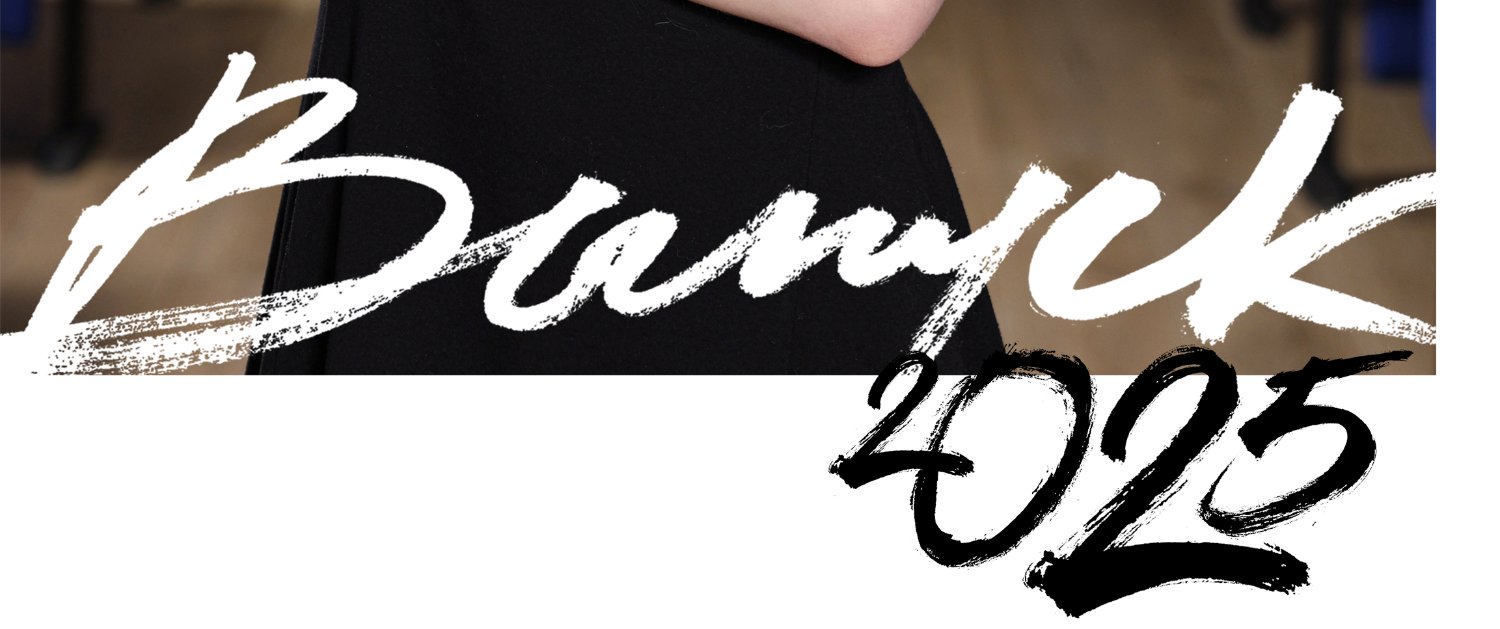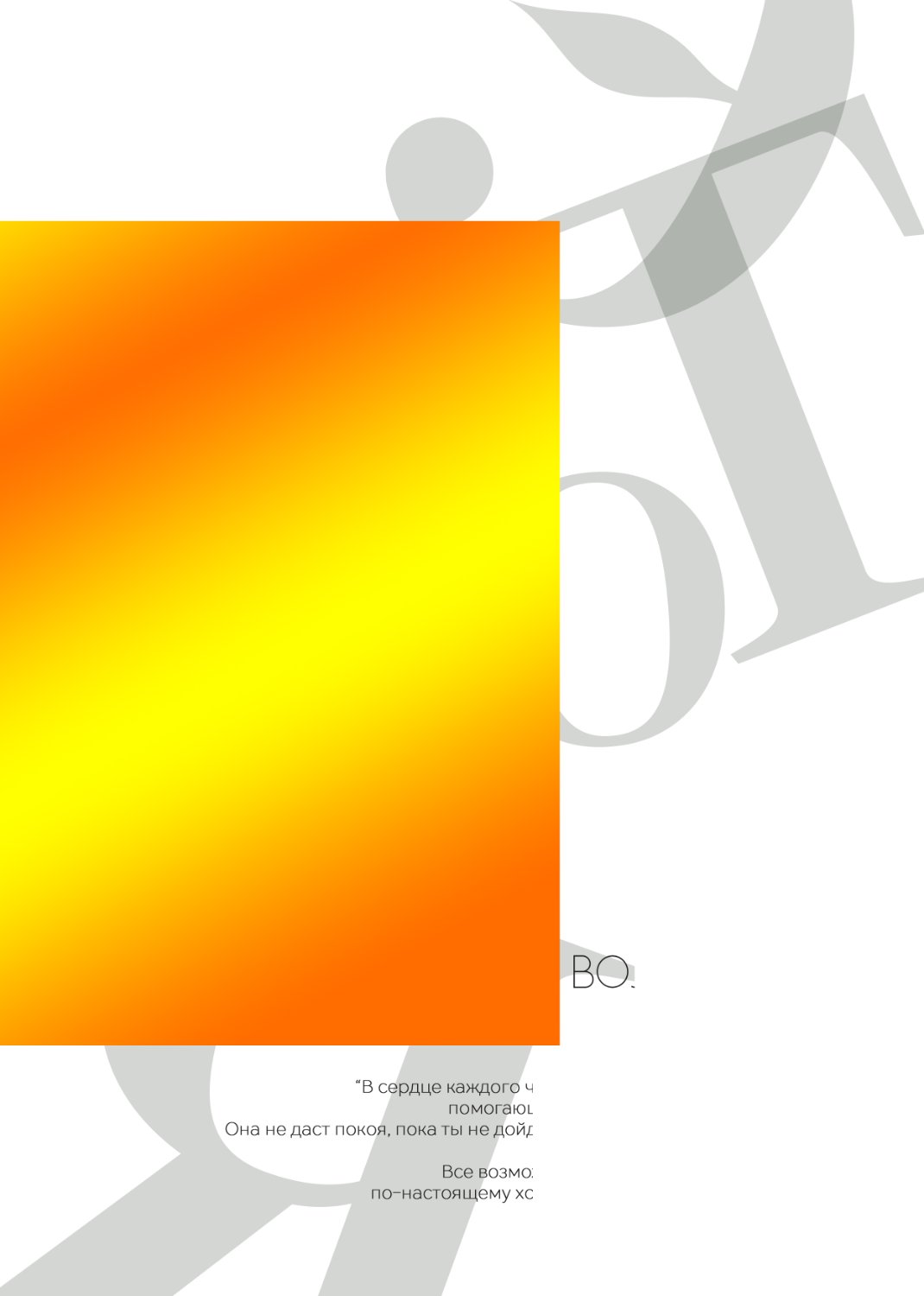
Помогите найти шрифты
Здравствуйте! Помогите пожалуйста найти шрифты! На второй картинке нужен тот что на фоне серый.
На второй картинке нужен тот что на фоне серый.
Картинки откуда, есть вектор/PDF, оранжевый прямоугольник зачем или так и было?
Покажите в исходном виде если есть, сейчас ни одной буквы не видно полностью.
Хотя там буква Ээ специфическая, может кто-то вспомнит, средний штрих необычный.
Первый похож на Pedell но не он:)